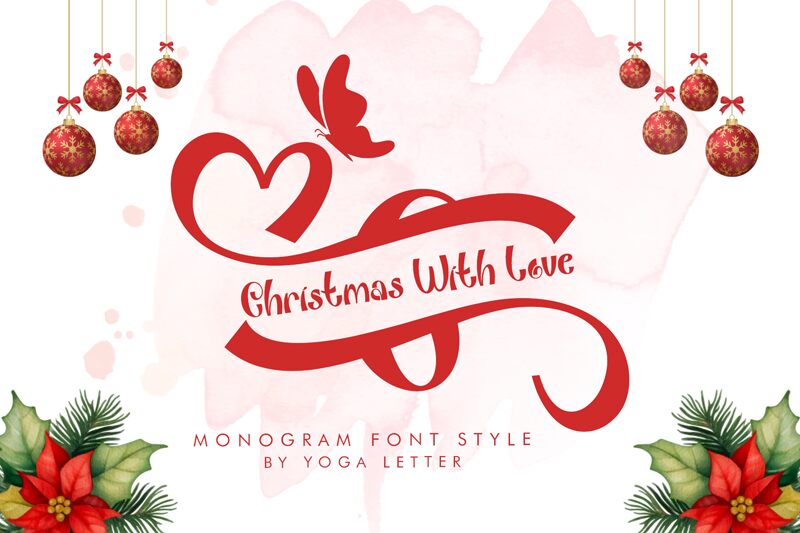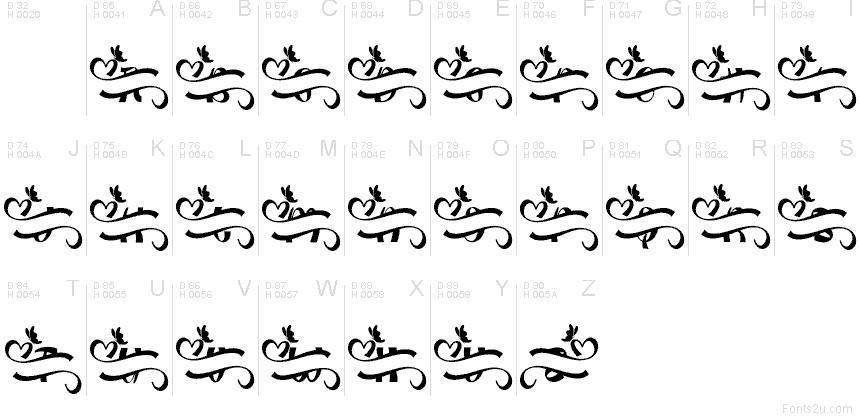
Christmas With Monogram
La tipografía Christmas With Monogram de Yoga Letter es una fuente navideña gratuita con adornos en forma de corazón, largas cintas fluidas y un pequeño detalle tipo mariposa que le confiere un estilo de ornamentación dibujada a mano. Sus líneas se curvan en amplios bucles y remates, logrando un efecto más decorativo que literal, con un motivo estacional que funciona perfectamente como detalle festivo.
Christmas With Monogram es ideal para tarjetas navideñas, etiquetas de regalo, bordes de invitaciones, papelería, logotipos y etiquetas de temporada, ya que sus trazos conectados enmarcan iniciales y nombres cortos sin necesidad de decoración extra. Esta fuente gratuita también encaja a la perfección en páginas de scrapbooking, gráficos para redes sociales, sellos de empaques y monogramas personalizados cuando buscas un toque festivo que acompañe al texto en lugar de competir con él.